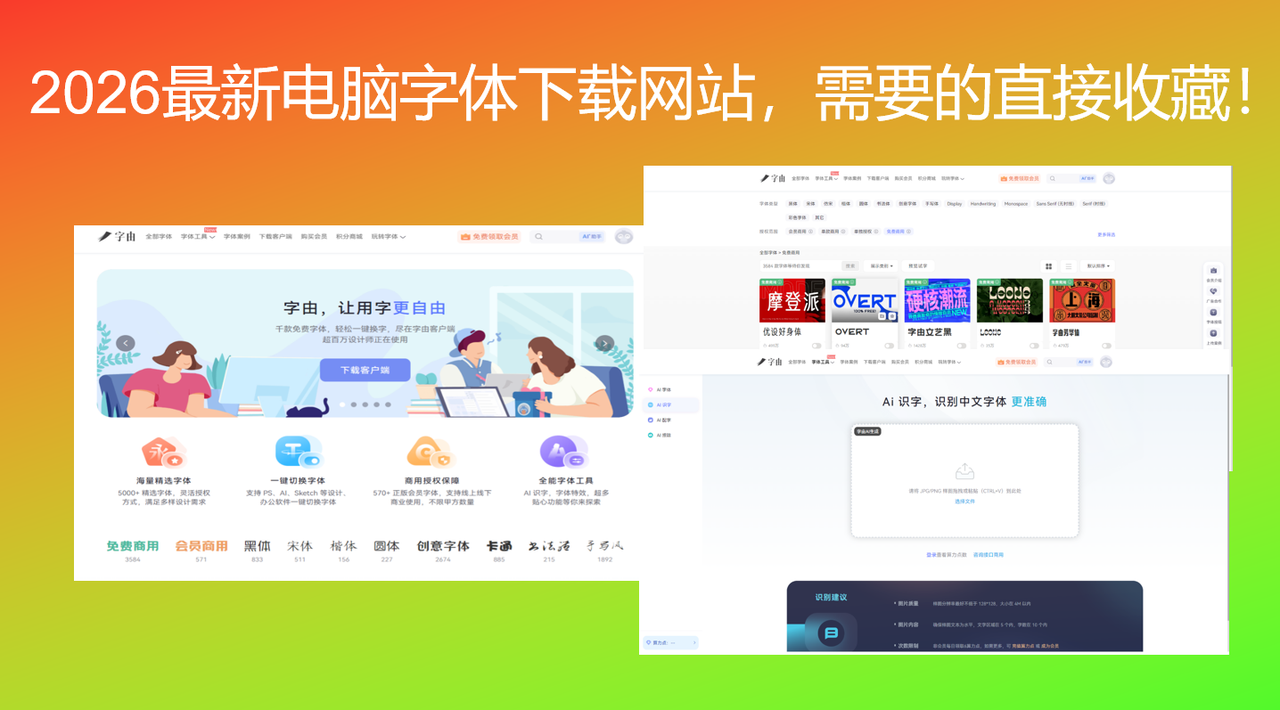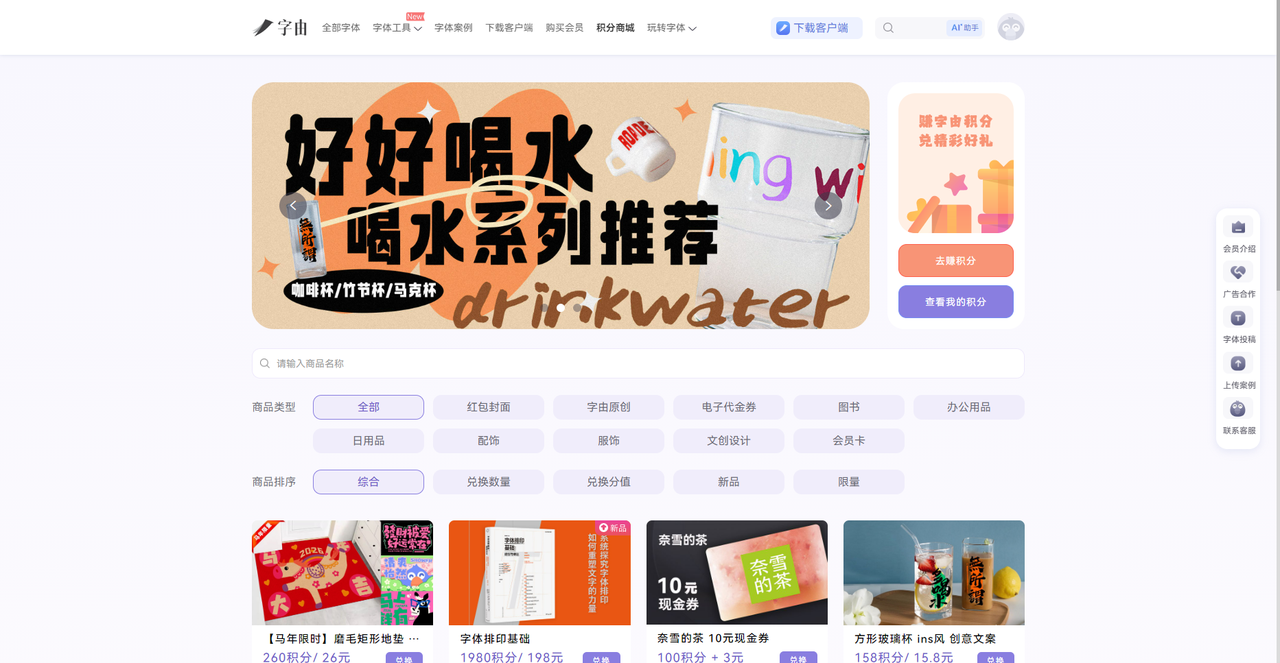
2026最新电脑字体下载网站,需要的直接收藏!
每次整理收藏夹,都会发现几个不怎么用得到的字体网站,偶尔点击去一看还会发现域名过期了无法打开。其实做设计这一行找字体本来就是需要耗费时间的工作,不过就算是直接去网站上搜索“电脑字体下载网站”,多半也都不怎么好用。那今天我就为各位设计师们总结了 2026 最新的电脑字体下载网站,需要的可以直接收藏码住!
第一个要推荐的就是字由,这也是我日常用的最多的一款电脑字体下载网站。不过它的客户端要比网页版的功能多一些,用起来也会更加便捷。最主要的是,它和普通电脑字体下载网站不同的是,它有 10500 多款字体,网站本身就相当于一个巨大的字体库,而且你还不需要一个一个下载、安装,打开客户端就能用。那么如果用字由找到并使用字体呢?下面我有详细的步骤:
- 筛选字体:点开“全部字体”,左侧有详细的筛选栏,按类型(黑体/宋体/书法体)、按授权(免费商用目前有3584款)、按热度(每款字体有使用次数)快速定位,总字体有 10500 多款,总会有你想要的那款字体。虽然有一部分是会员专享,但是大可放心,字由不会变相做强制用户消费的事情,字由里面大部分的字体就足够普通用户使用了。
- 预览试字:点击感兴趣的字体,输入自己的文字实时看效果,不用下载就知道合不合适。
除此之外,字由还有个人云字库、AI 智能工具和支持团队字库等实用功能。而且字体还有专门的积分商城板块,商品类型从红包封面再到文创设计,甚至还有日用品以及服饰等相关设计,这些商品都是可以用积分来兑换的,你在里面甚至还可以看到奶茶品牌的现金券,要知道这是个字体网站,功能和涉及板块之齐全让人直呼惊喜,如果你也想来探索更多关于字由的内容,来官网立刻试试吧!
2、Alkes
接下来我要介绍的这款电脑字体下载网站是一个精品字体销售平台,里面都是精品字体在折扣促销,我时不时就会来这个网站看两眼有没有能用得上的,平时很贵但是这时候却打折了的商品,因为这里面几乎每一款在售的字体质量都非常高,如果要我推荐的话我会选择 POSTAMP GROTESK、Trifyx 和 Nexa Pro。这个网站比较适合需要购买高品质商业字体的设计师,虽然大部分需要付费,但经常有折扣,性价比不错。作为电脑字体下载的补充渠道,可以关注。
3、Source Sans Pro(Adobe Fonts)
这个电脑字体下载网站是 Adobe 出品的经典开源无衬线字体。它有多种字重:Regular、Bold、Light、Semibold、ExtraLight、Black 等,还有对应的斜体版本。虽然页面看起来比较简单但是 Source Sans Pro 是真正免费可商用的电脑字体下载资源,可以在 Adobe Fonts 平台直接下载,或者通过字由一键调用。它线条清晰、可读性强,适合正文排版、UI 设计、办公文档等场景。
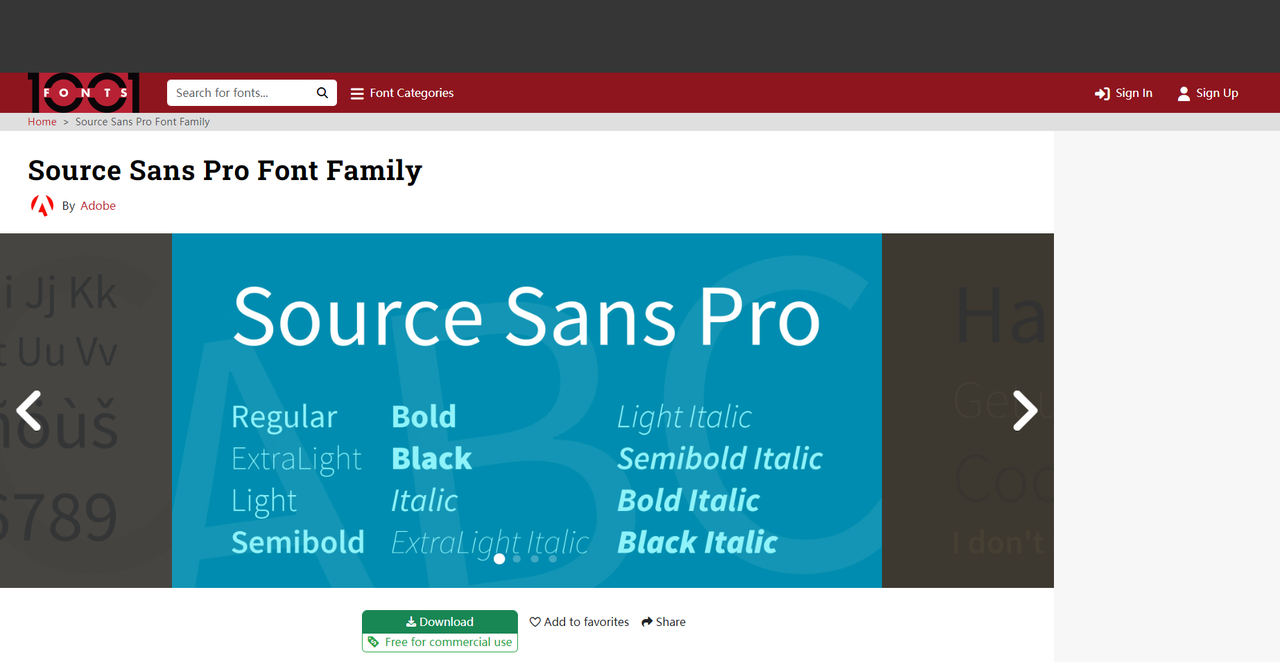
4、Cufon Fonts
Cufon Fonts 这款老牌电脑字体下载网站界面简洁,分类清晰。首页顶部有 Serif、Sans-Serif、Display、Handwritten、Monospaced、Symbol 等常用分类,方便快速搜索。我推荐这个网站的主要原因是它有专题合集能工,从主页就可以看到它整理了各种主题的字体合集,比如 Science Fonts、Typography Fonts、Tattoo Fonts 等,并且每个合集都有几十到上百款字体,点进去就能浏览。但是需要注意的是,有些字体会标注“Free for personal use”,下载前记得查看具体授权说明。
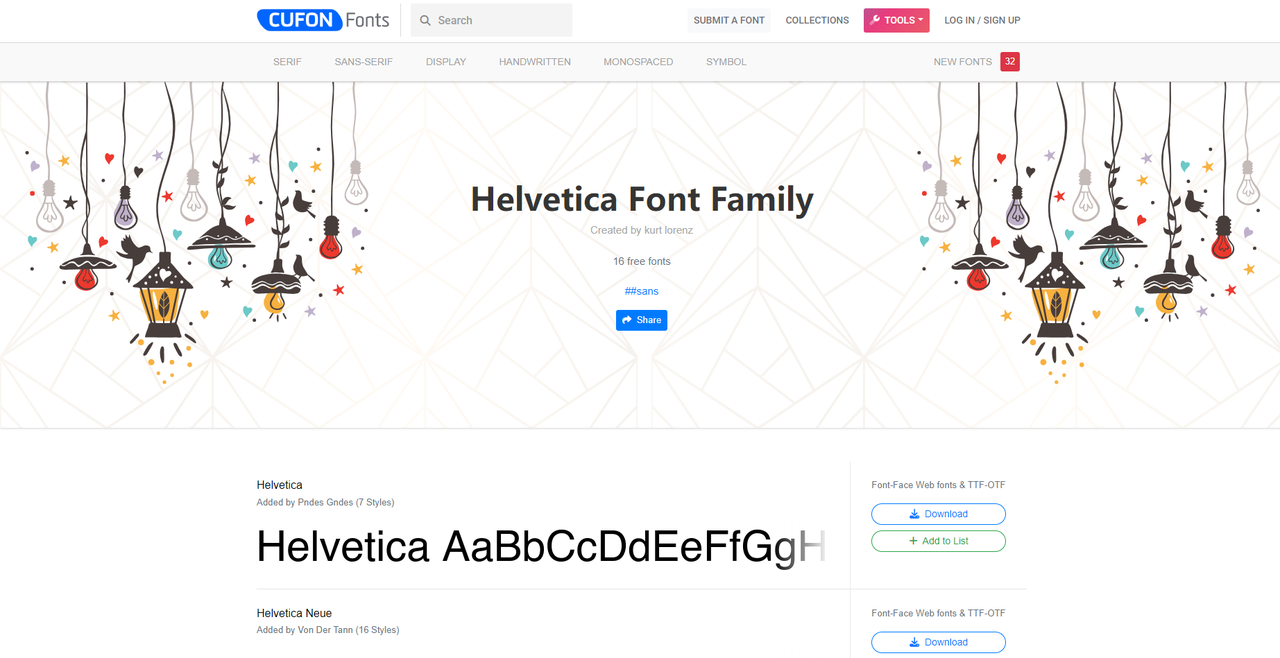
5、FontRiver
FontRiver 从2000年左右就开始运营,积累了大量的字体资源,也算是一个老资历的电脑字体下载网站了,而且可以看到首页顶部写着“TONS OF FREE DOWNLOADABLE FONTS”(海量免费可下载字体),定位非常明确。这个网站的分类也非常多样,你可以按字母排序寻找,也可以按风格和字体代工厂寻找,并且右侧还会给你推荐其他字体网站,如果这个网站中没有你喜欢的还可以顺带逛一下隔壁网站,总之肯定是会有收获的!这里面我主要是推荐 Reality 和 Continuity 这两款字体。再者,下载前一定要看清楚页面上的版权说明。虽然需要花点时间筛选,但这里确实能淘到很多其他网站找不到的小众字体。
这 5 个网站,其实代表了不同的字体需求,Alkes 适合愿意为设计付费的人,Source Sans Pro 是“少而精”的代表,Cufon Fonts 用专题合集帮你省时间,而字由像是一个工具箱,把字体相关的功能统统打包进了一个网站里,一站式解决你的字体需求,最主要的是大部分字体都是免费使用的,说到底,工具再多,顺手最重要。如果你也在找一个能长期用下去的字体网站,不妨从字由开始试试。